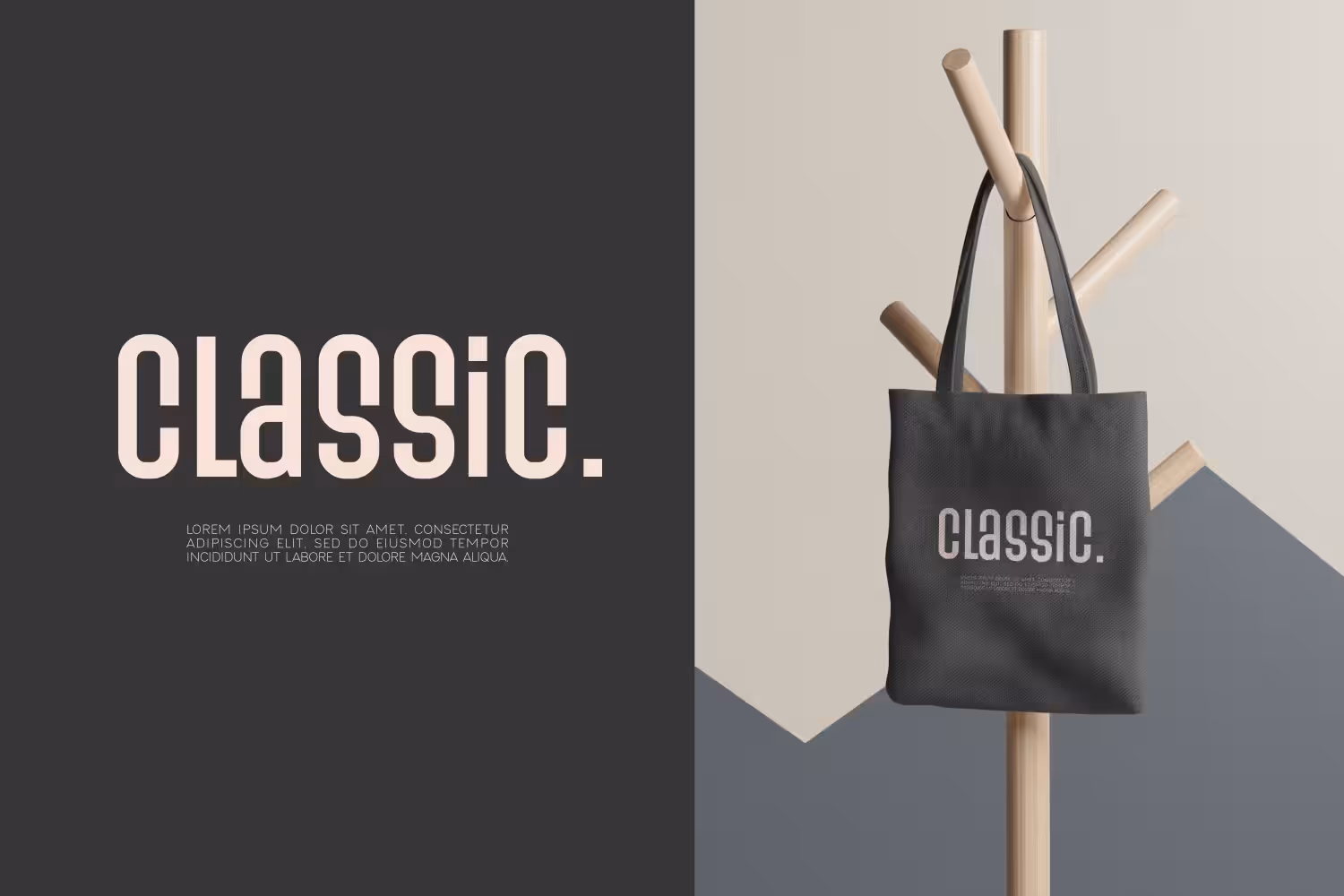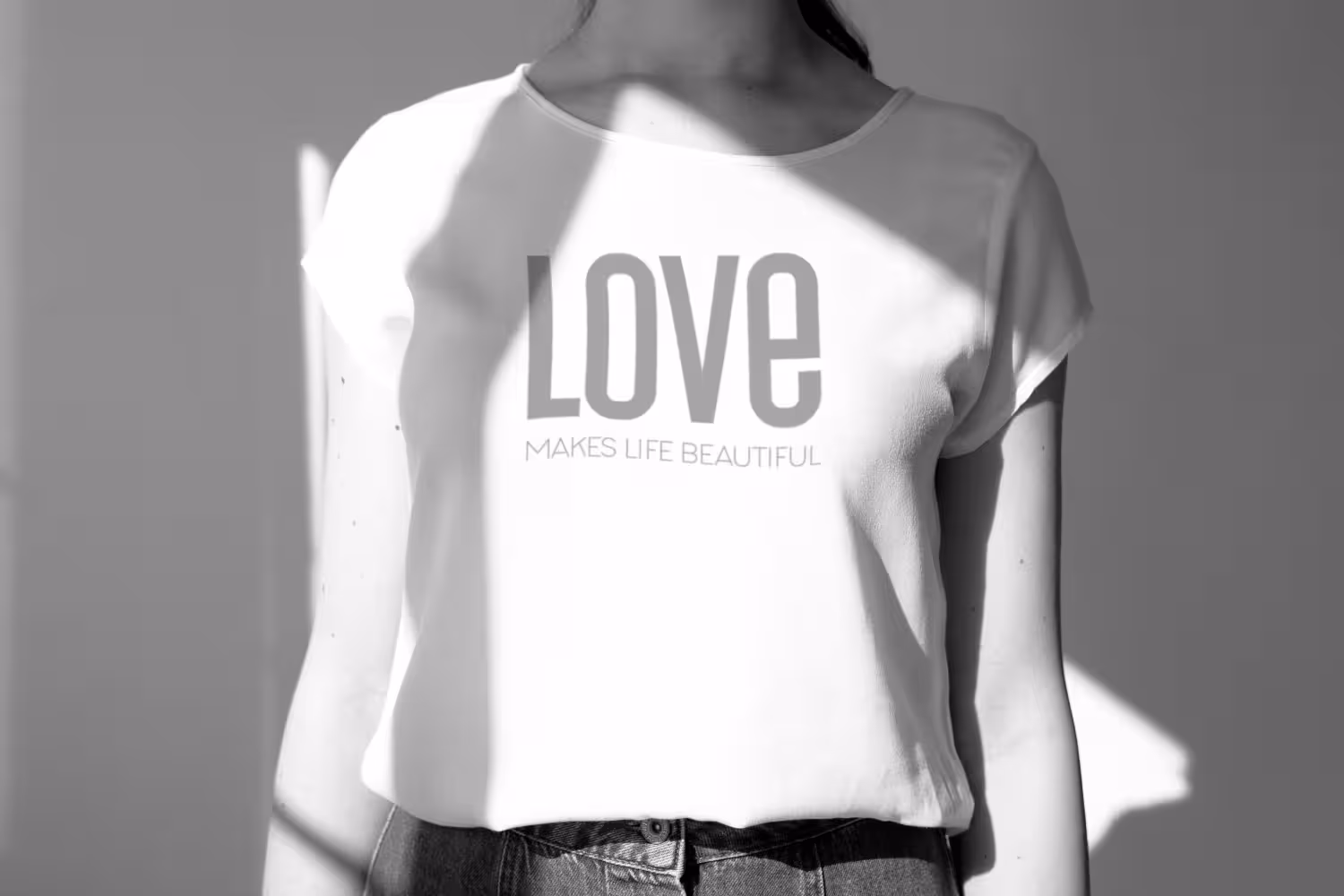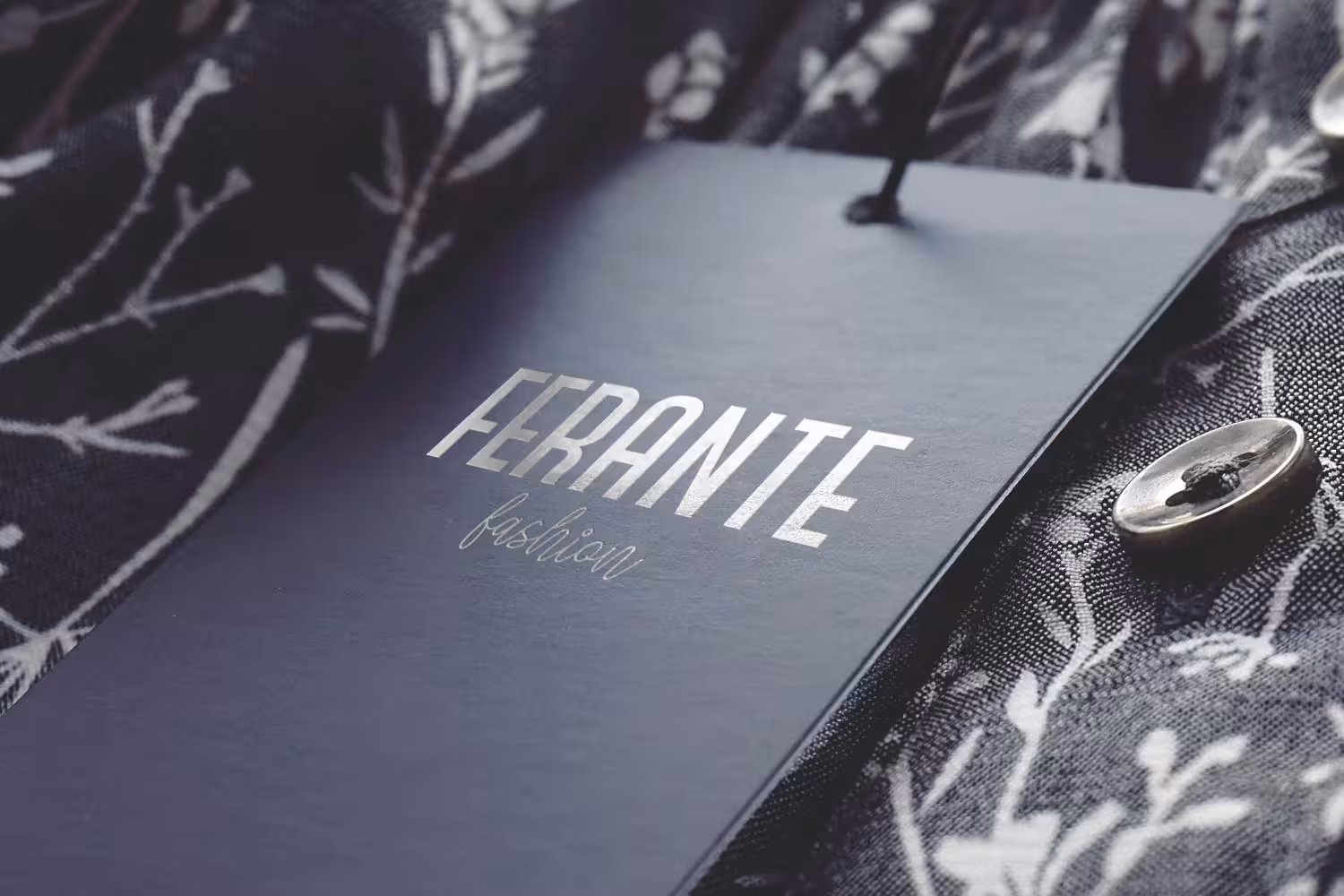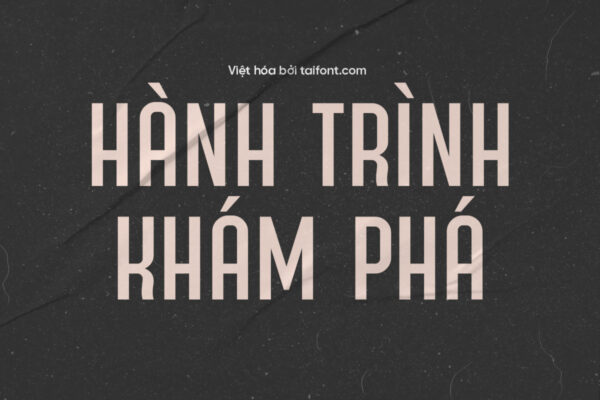
Giới thiệu về Font TF Modern Luxury Việt hóa
TF Modern Luxury Việt hóa là một font chữ không chân (sans-serif) nổi bật với thiết kế cao, thanh lịch và mang đậm vẻ đẹp hiện đại, sang trọng. Font này toát lên phong thái tinh tế, tối giản nhưng đầy cuốn hút, lý tưởng để tạo nên sự độc đáo và đẳng cấp cho mọi thiết kế.
Với đặc điểm là dáng cao, nét thanh và tính thẩm mỹ cao, Modern Luxury là lựa chọn lý tưởng cho các thiết kế muốn truyền tải sự hiện đại, sang trọng và phong cách:
- Thiết kế thời trang: Hoàn hảo cho các thương hiệu thời trang cao cấp, từ logo, nhãn mác sản phẩm, lookbook, đến các chiến dịch quảng bá bộ sưu tập. Font này giúp truyền tải vẻ đẹp thanh lịch, đẳng cấp và độc đáo của trang phục, nâng tầm giá trị thương hiệu.
- Thiết kế túi vải (canvas): Lý tưởng để in các tên thương hiệu, slogan, hoặc các câu trích dẫn mang phong cách tối giản, hiện đại lên túi vải canvas. Nét cao và thanh của font sẽ làm cho chiếc túi trở nên cá tính, phong cách và thu hút sự chú ý.
- Thiết kế nhận diện thương hiệu: Phù hợp cho các logo, tagline hoặc bộ nhận diện thương hiệu muốn truyền tải sự hiện đại, tinh tế và uy tín. Modern Luxury giúp xây dựng một hình ảnh thương hiệu vững chắc và dễ nhận diện.
- Thiết kế tạp chí và ấn phẩm cao cấp: Thích hợp cho các tiêu đề, nội dung bài viết trong các tạp chí về thời trang, lối sống, hoặc kiến trúc, nơi cần sự sang trọng và rõ ràng.
Với TF Modern Luxury Việt hóa, bạn có thể dễ dàng thổi hồn hiện đại, sự tinh tế và sang trọng vào các thiết kế, tạo ra những sản phẩm không chỉ đẹp mắt mà còn đầy cảm xúc và sức hút đặc biệt.